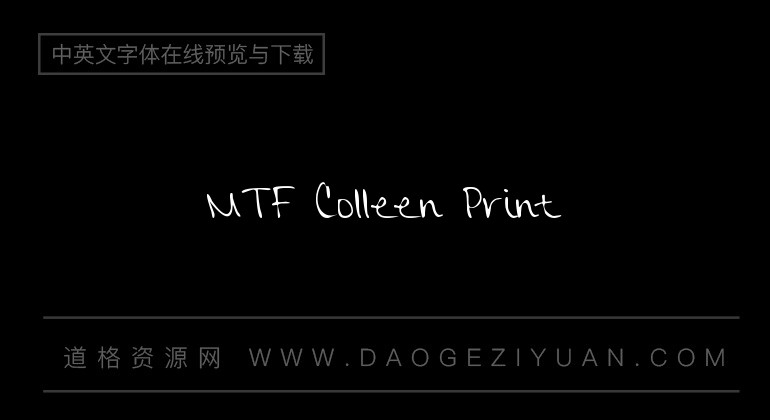
? MTF Colleen Print 字体是一款设计精美的手写体字体,适用于商业和个人项目。它具有细腻的手写笔触,以及清晰的英文字母,数字和标点符号,使其适用于各种场景。它具有独特的细节,可以为您的设计添加一些特色,并使其显得更加个性化。此外,MTF Colleen Print 字体还具有多种字重,可以满足您的不同需求,使您的设计更加丰富多彩。内容介绍
MTF Colleen Print是一款非常不错的手写艺术字体,具有很好的视觉感,适合于文化类的宣传设计、商业类品牌的广告和产品包装设计以及个性化文字排版等较多场景。